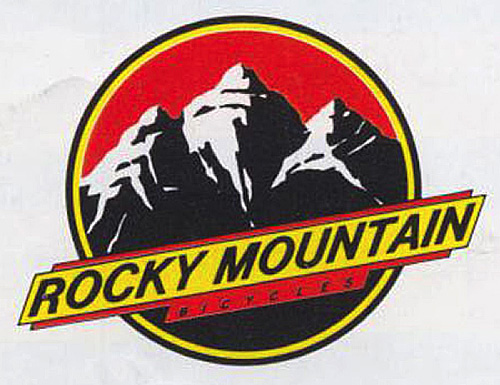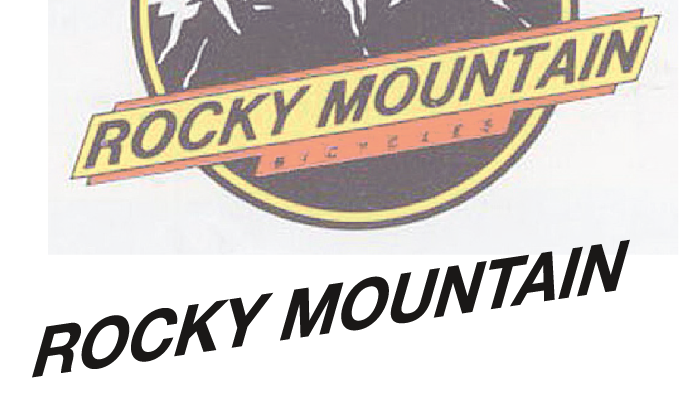
Typo des alten Rocky Mountain-Logos gesucht
Eine verbogene Helvetica?
Dachte ich auch erst. Aber C, K, M und O sehen anders aus.
Was aber natürlich wirklich irgendwie gebastelt und verzerrt
sein könnte ...
Anders? Ich hab das mal schnell aus der Helvetica 75 Bold hingebogen:
Geht doch, oder?
Stimmt! Du hast also die Helvetica 75 gekippt und noch etwas gestaucht oder?
Das K sieht wahrscheinlich nur so komisch aus, weil die Qualität so schlecht ist. Warscheinlich ein Scan ...
Auch sonst ist die Grafik wohl ein eher mäßiger Nachbau ... denke nicht, dass im ursprünglichen Logo die Buchstaben vereinzelt nach oben und unten verteilt rumhüpfen. Bei ROCKY z.B. das O & C.
Stimmt! Du hast also die Helvetica 75 gekippt und noch etwas gestaucht oder? :cheer:
Nee, ich hab sie verbogen, verzogen, geneigt, gedreht, gestaucht, gequetscht und gekippt :D